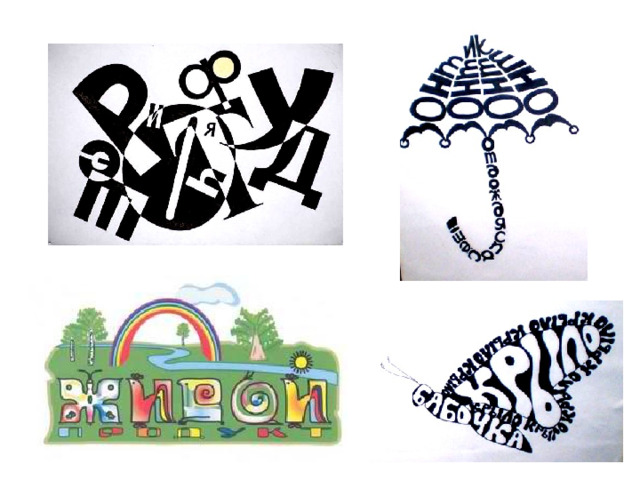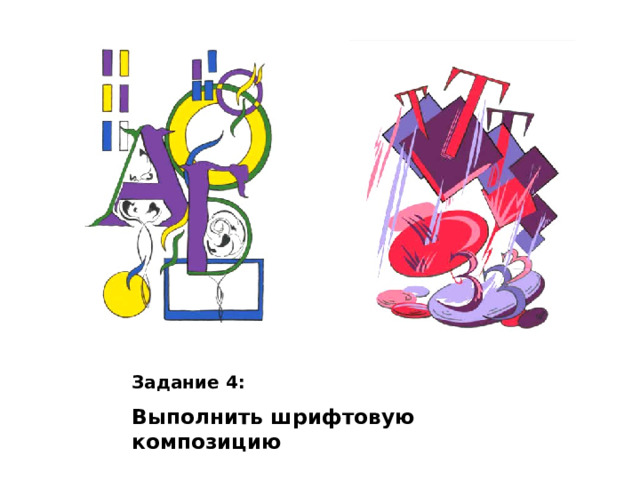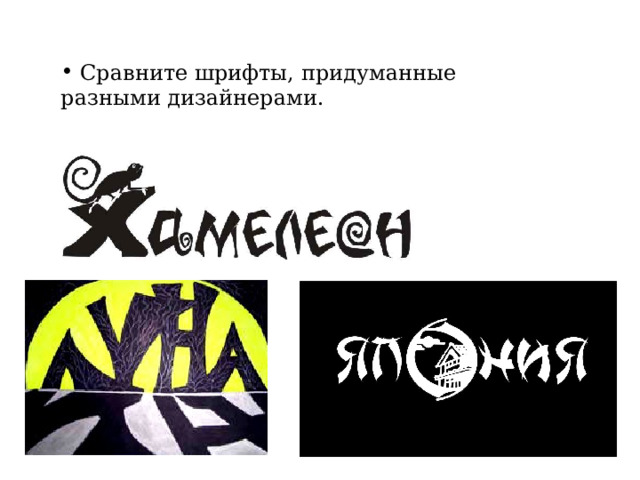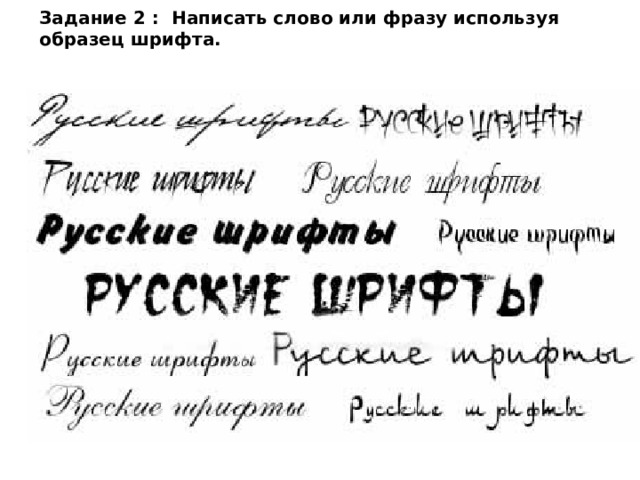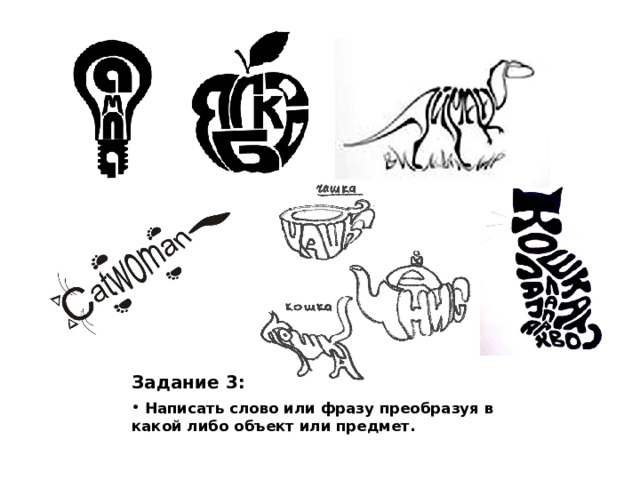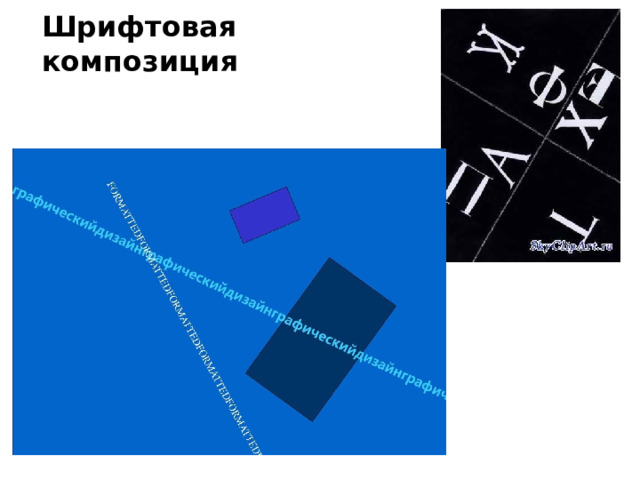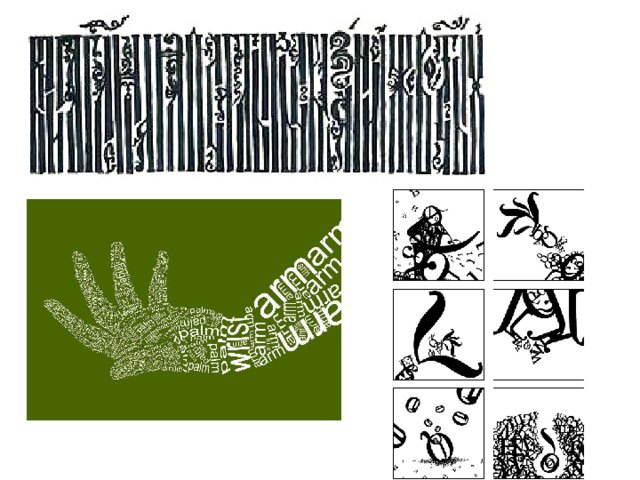
Искусство шрифта Урок изобразительного искусства В 7 классе
Искусство шрифта
Урок изобразительного искусства
В 7 классе
Любая буква или иероглиф прежде всего изображение. Буква ведет свою родословную от рисунка. В глубокой древности всю информацию обозначали рисунками. Потом рисунки превратились в первые буквенные символы, которые стали основой написания современными буквами.
• Любая буква или иероглиф прежде всего изображение. Буква ведет свою родословную от рисунка. В глубокой древности всю информацию обозначали рисунками. Потом рисунки превратились в первые буквенные символы, которые стали основой написания современными буквами.
Сравните шрифты, придуманные разными дизайнерами.
• Сравните шрифты, придуманные
разными дизайнерами.
Сравним линейные композиции из узорчатой полоски, прямой линии, буквенной строки и убедимся, что в отличии от линии и полоски строка имеет смысл, т.е. несет информацию. Но изобразительного различия между линией и строкой нет. Как элементы композиции они играют одинаковую роль.
• Сравним линейные композиции из узорчатой полоски, прямой линии, буквенной строки и убедимся, что в отличии от линии и полоски строка имеет смысл, т.е. несет информацию.
Но изобразительного различия между линией и строкой нет. Как элементы композиции они играют одинаковую роль.
Задание 1 : Написать 10 букв используя образец.
Задание 1 :
Написать 10 букв используя образец.
Задание 2 : Написать слово или фразу используя образец шрифта.
Задание 3:  Написать слово или фразу преобразуя в какой либо объект или предмет.
Задание 3:
• Написать слово или фразу преобразуя в какой либо объект или предмет.
Шрифтовая композиция
Задание 4: Выполнить шрифтовую композицию
Задание 4:
Выполнить шрифтовую композицию